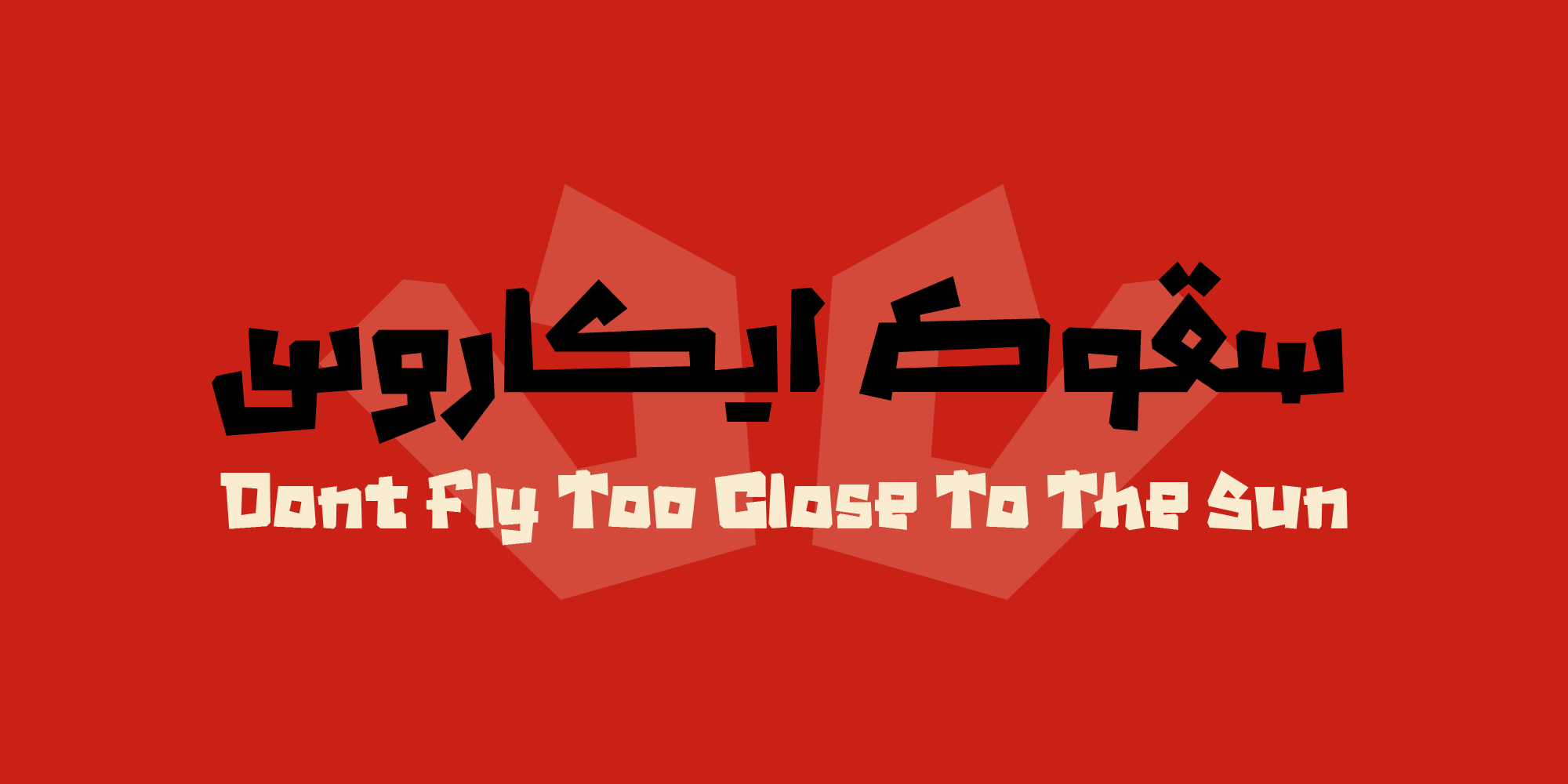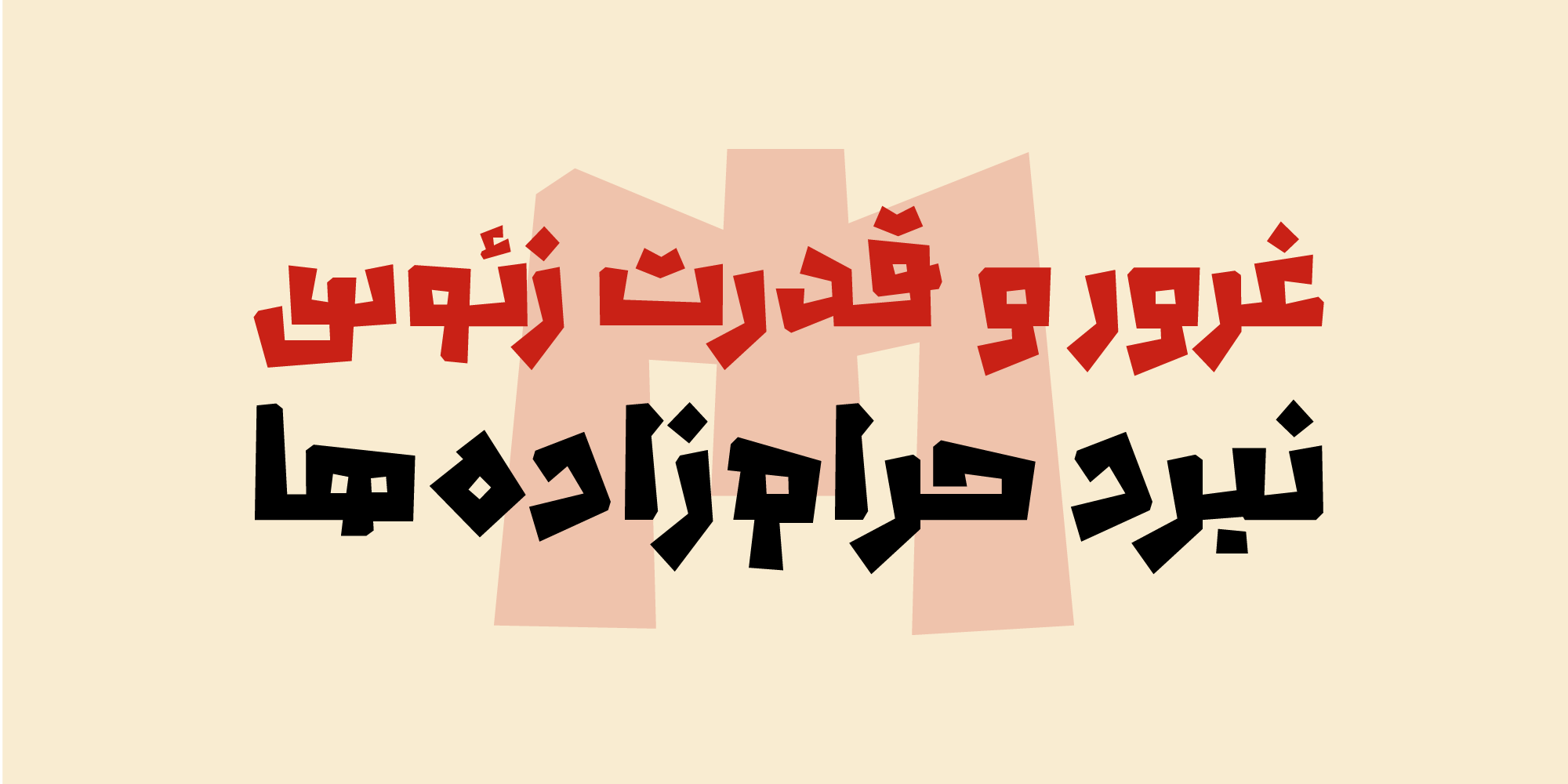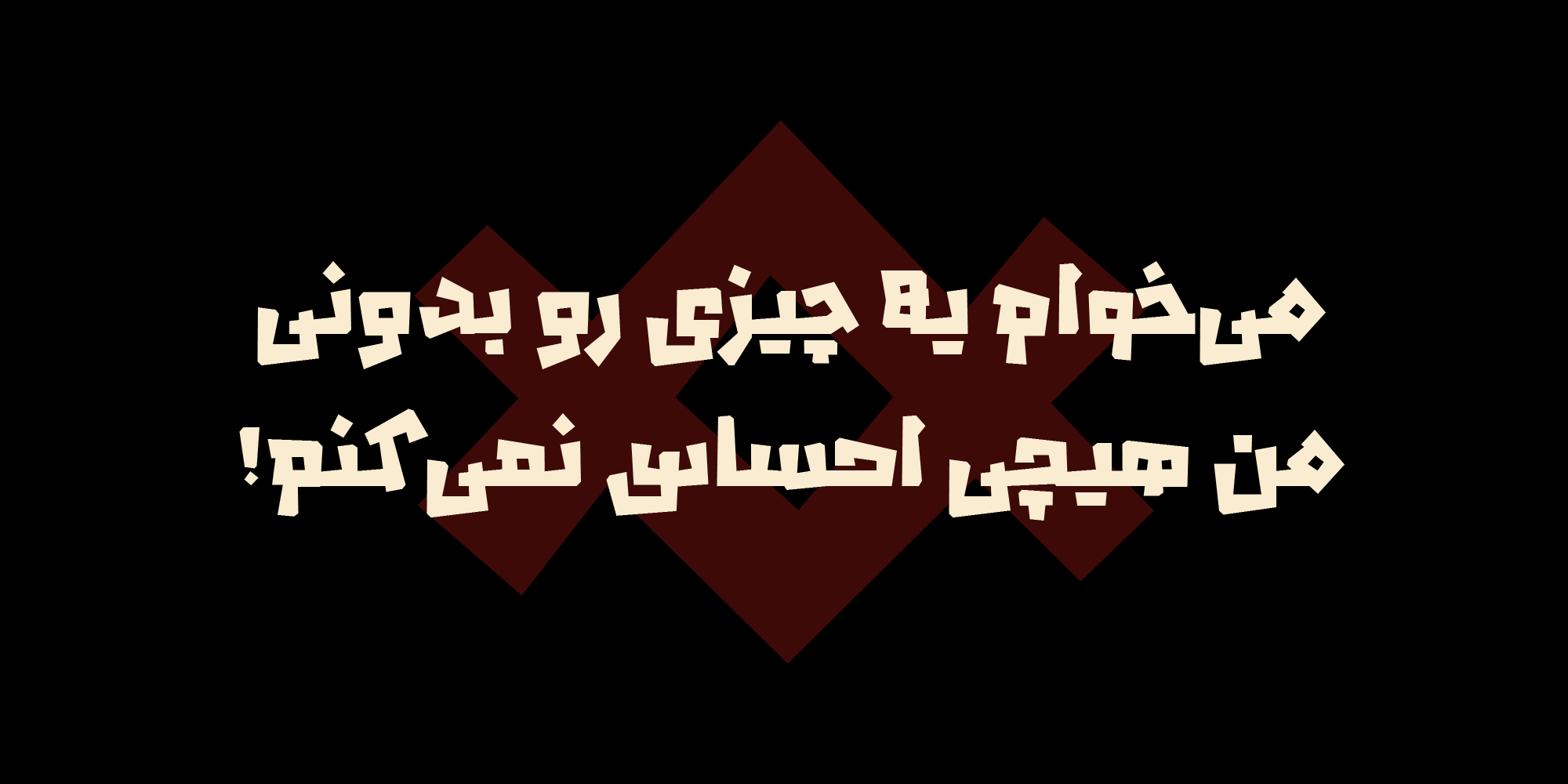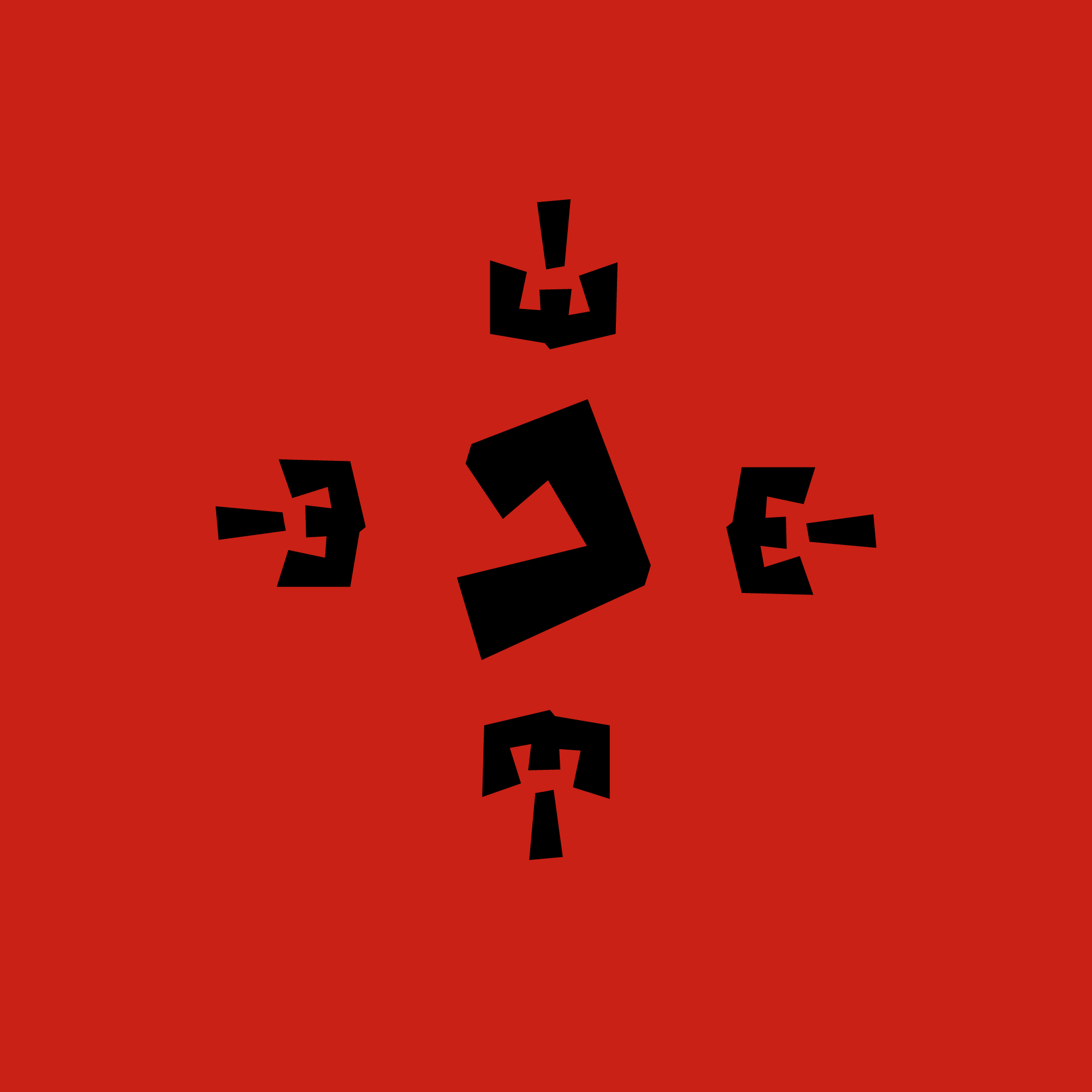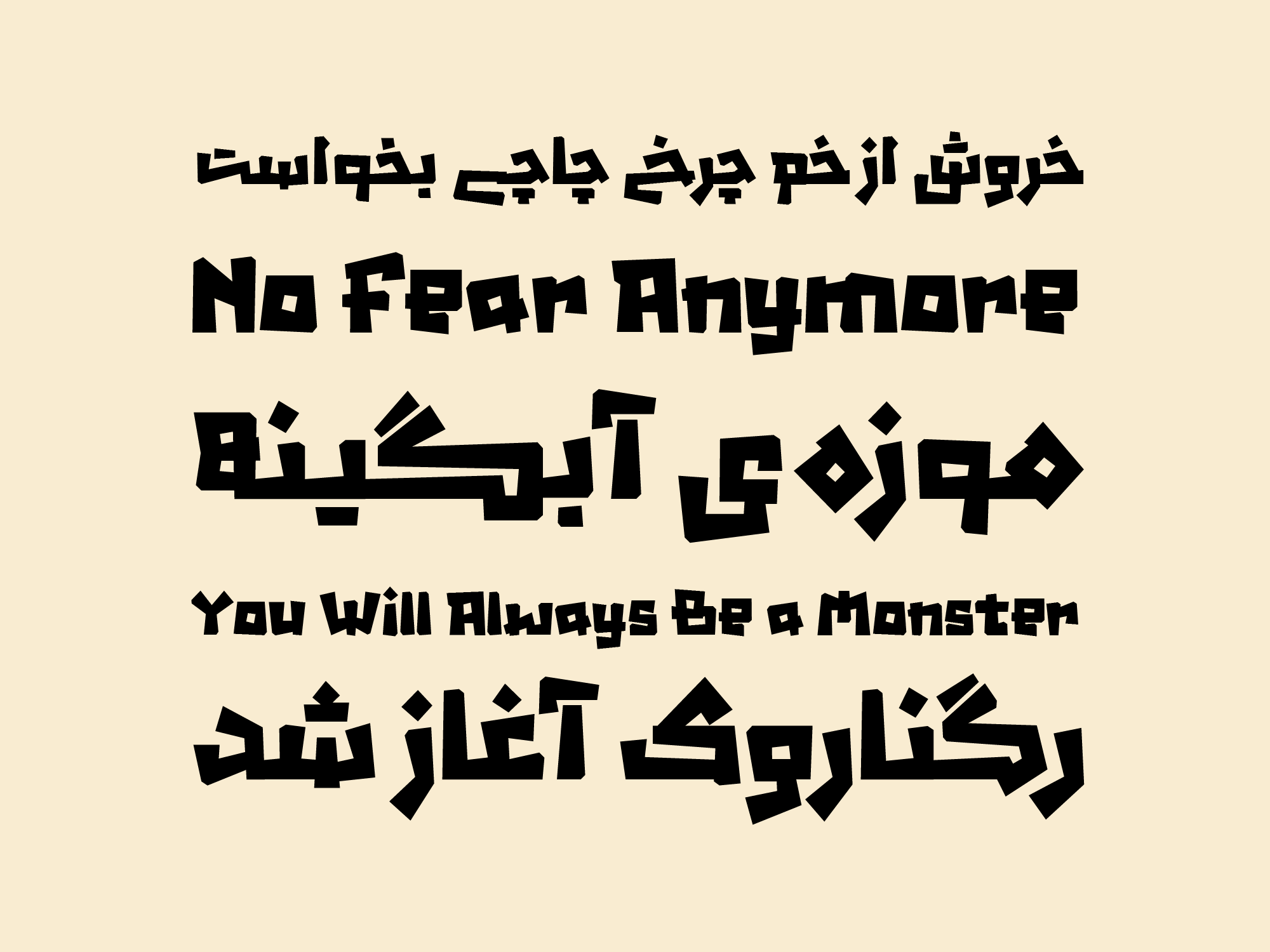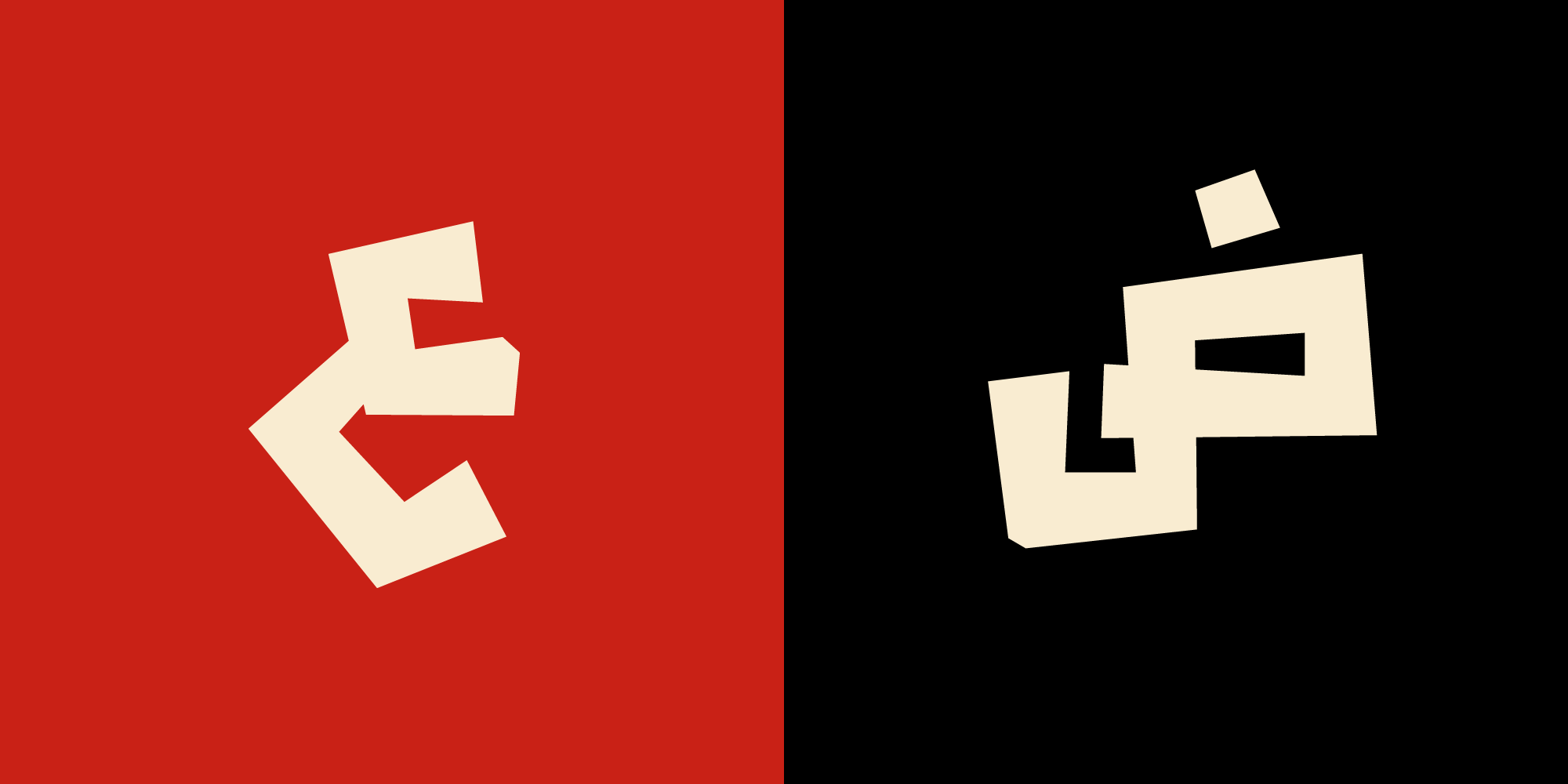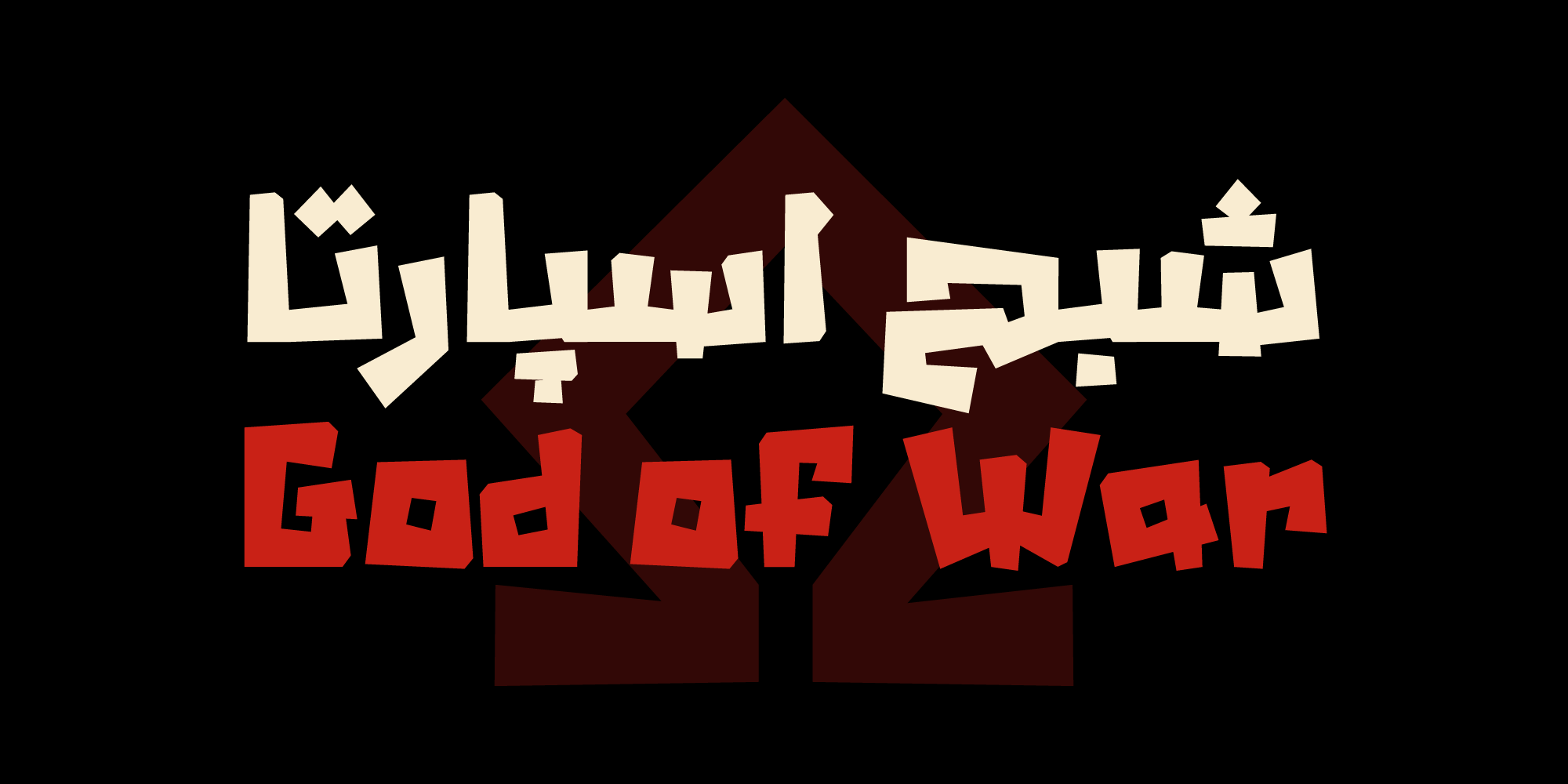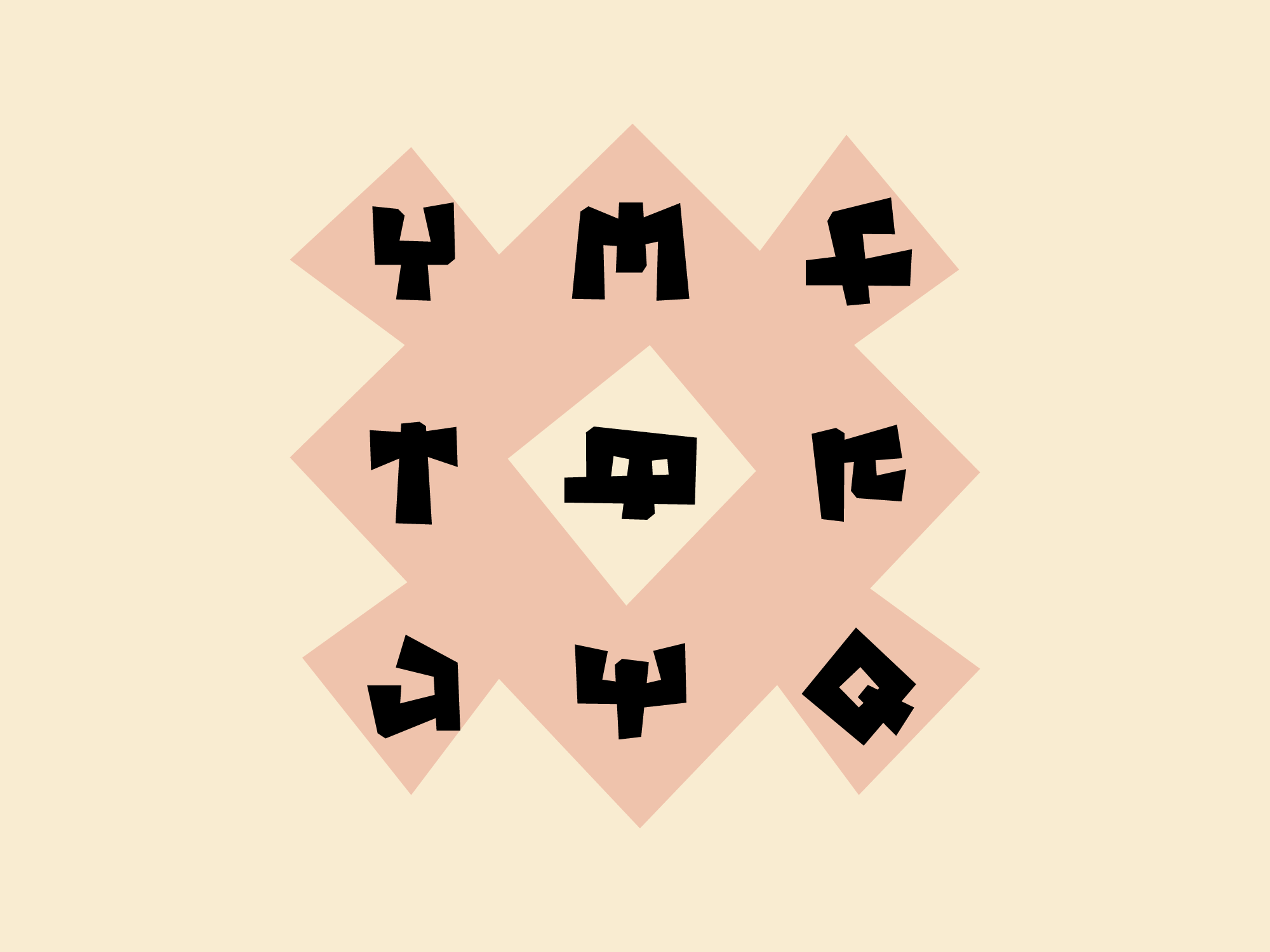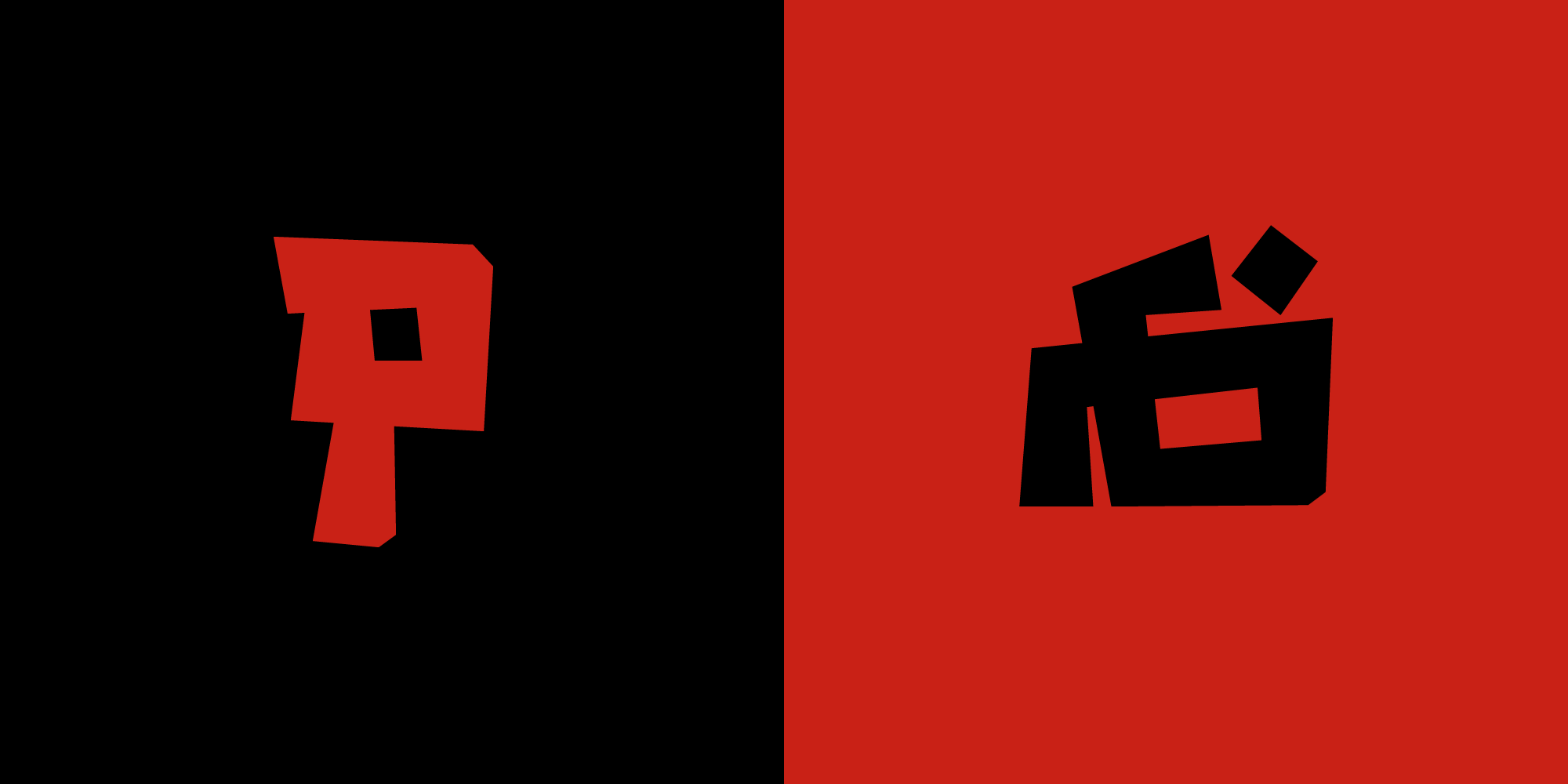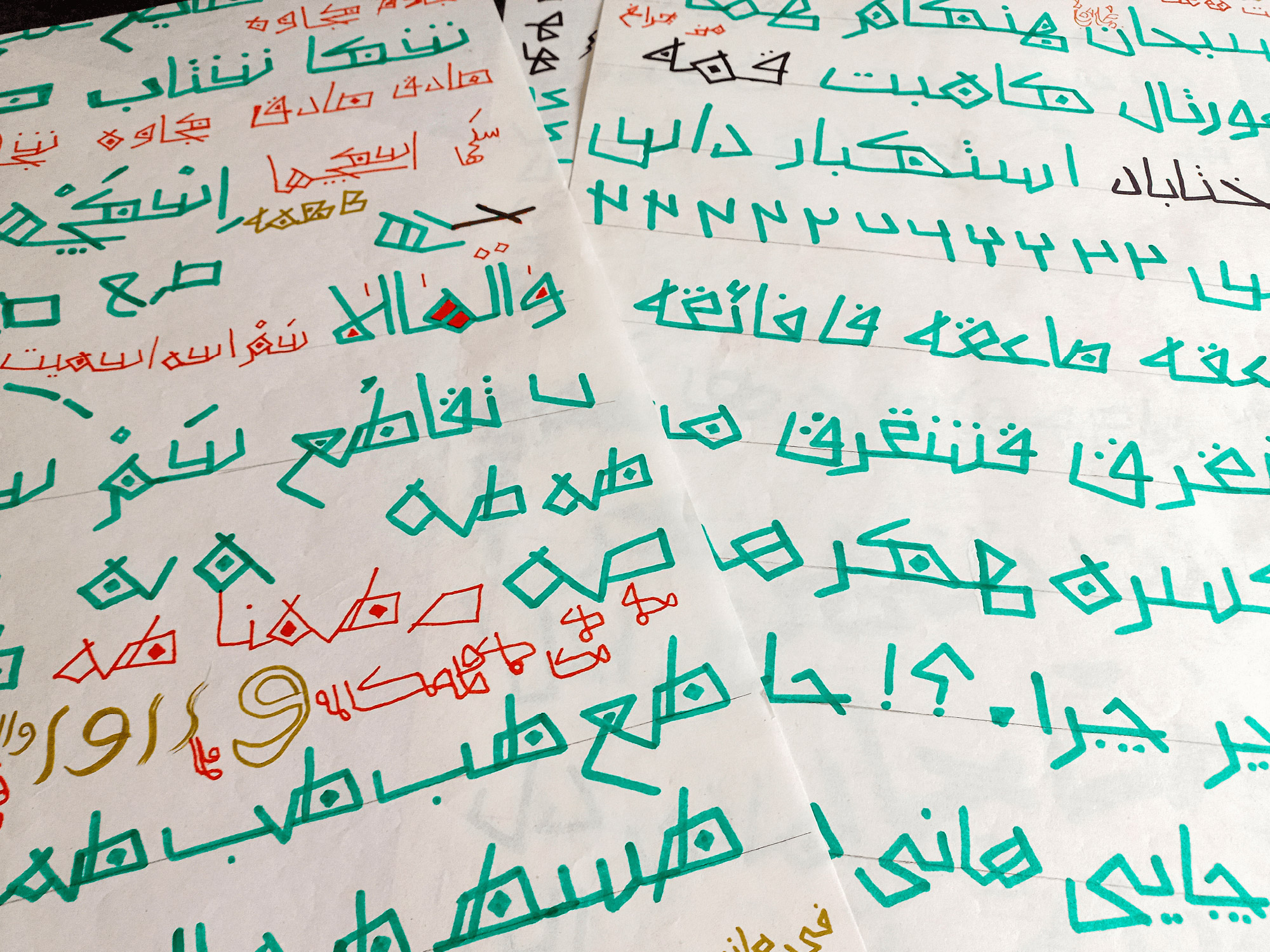
کاراکترست انگلیسی براساس حروف فارسی طراحی شده است.
در طراحی والهالا حتی حروف یکسان هم بااینکه رفتار مشابه دارند،با یکدیگر متفاوتند.
این تنوع فرم در نقطهها هم وجود دارد.
جایگزینها و ترکیبها
والهالا یک فونت نمایشی است؛ اما اگر نیاز به نمایش بیشتر باشد حروف جایگزین و ترکیبها امکانات بیشتری را برای این امر در اختیار کاربر قرار می دهند.
کشیدهها (Low swash)
خیلی کشیدهها (High swash)
پشتیبانی از زبانهای عربی، انگلیسی، اردو و کوردی